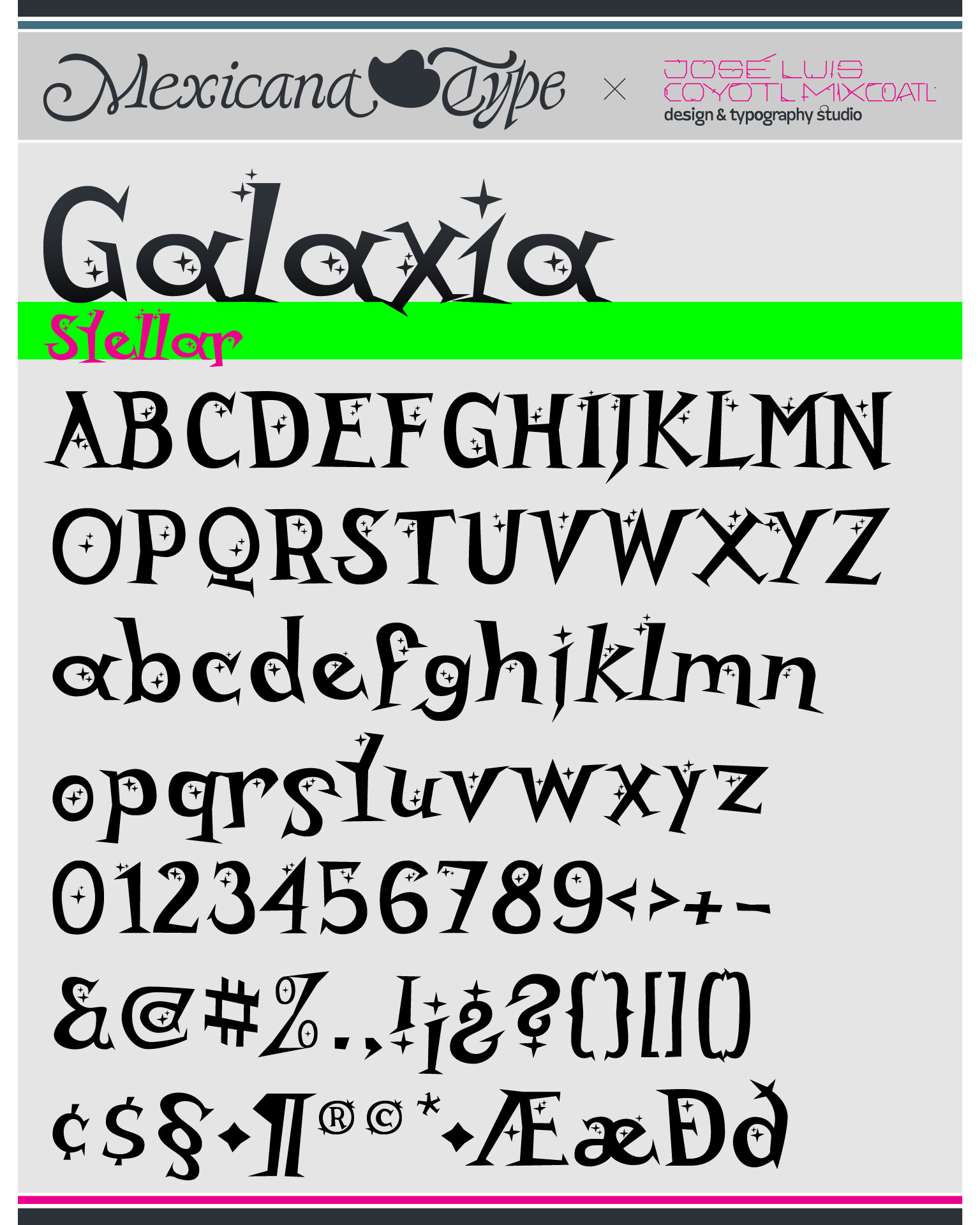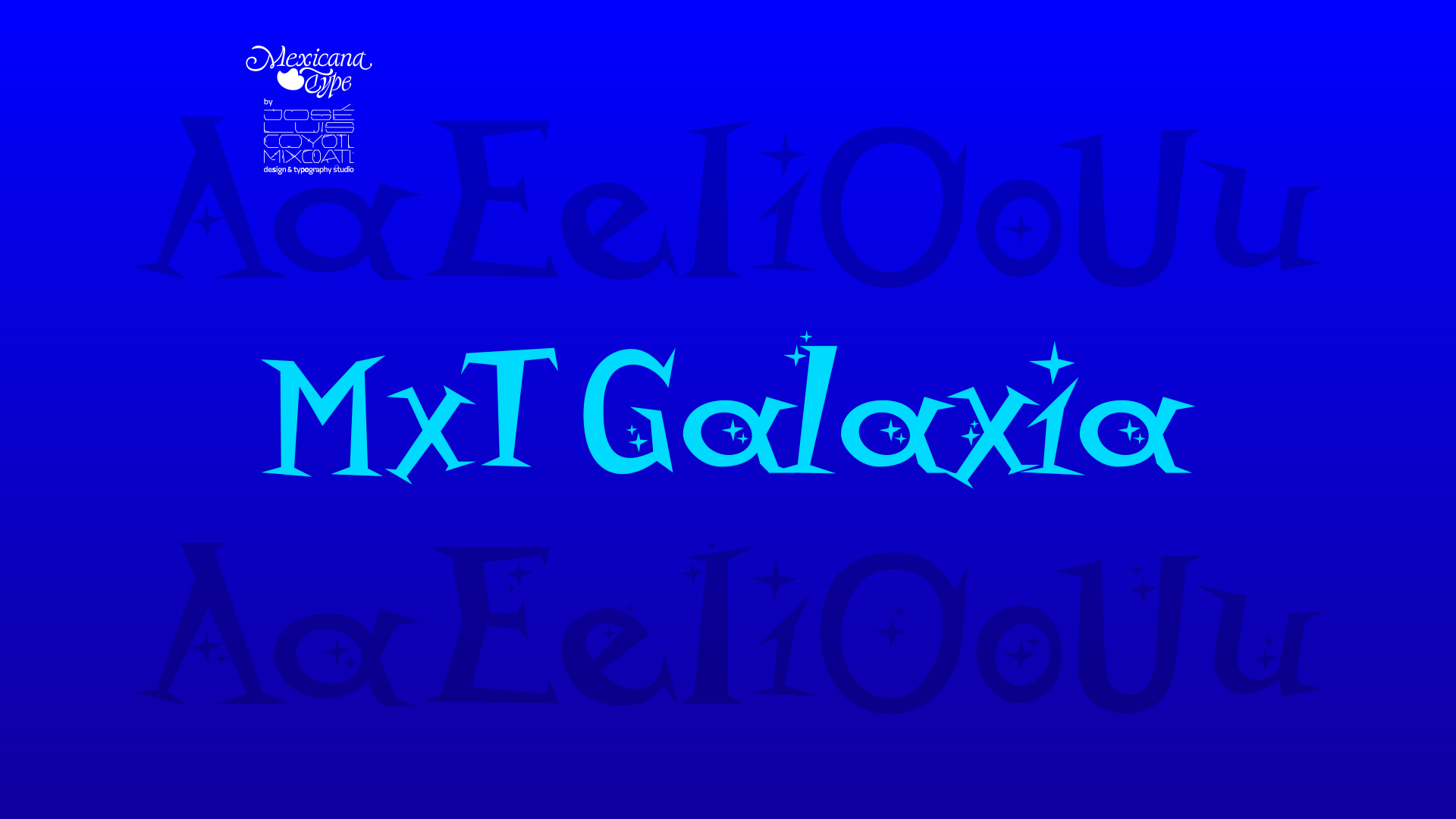
MxT Galaxia fue inspirada por dibujos animados y series de televisión con estética espacial, con un toque más relajado y un tanto con humor caricaturesco, pensada como una tipografía con apariencia de contrastes variados e irregulares en su estructura que generara un cuerpo de texto dinámico y estilizado. La aparente ausencia de una línea base y alturas X en sus altas y bajas tienen como intención la sensación de que las letras parezcan flotar y dar movimiento a los bloques de texto que van formando, que aunque si bien está pensada para palabras y frases cortas, también tiene su gracia en manchas de texto un poco más largos.
Sus ángulos agudos y cuerpo irregular son la constante que le da un sentido de uniformidad y textura discontínua, particularidades que se acentúan con detalles de pequeñas estrellas en su versión Stellar.